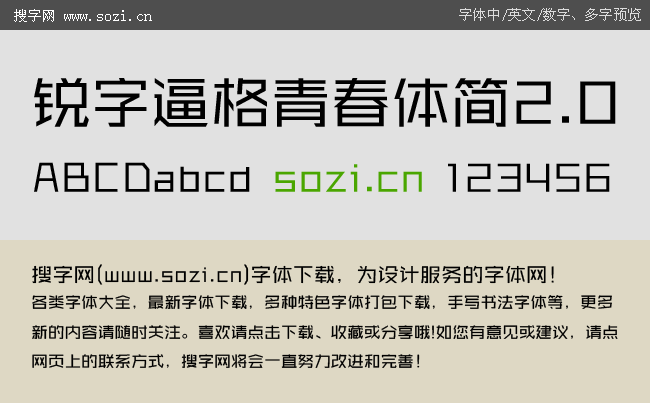
銳字逼格青春體簡(jiǎn)2.0
搜字網(wǎng)提供一款銳字逼格青春體簡(jiǎn)中文字體下載,銳字逼格青春體簡(jiǎn)是一款應(yīng)用于設(shè)計(jì)方面的中文簡(jiǎn)體漢字,該字體端正大方,擁有卡通風(fēng)格,整體效果非常出眾,并且字庫(kù)完整,可以應(yīng)用于廣告設(shè)計(jì)、名片設(shè)計(jì)、包裝印刷、產(chǎn)品設(shè)計(jì)等應(yīng)用。